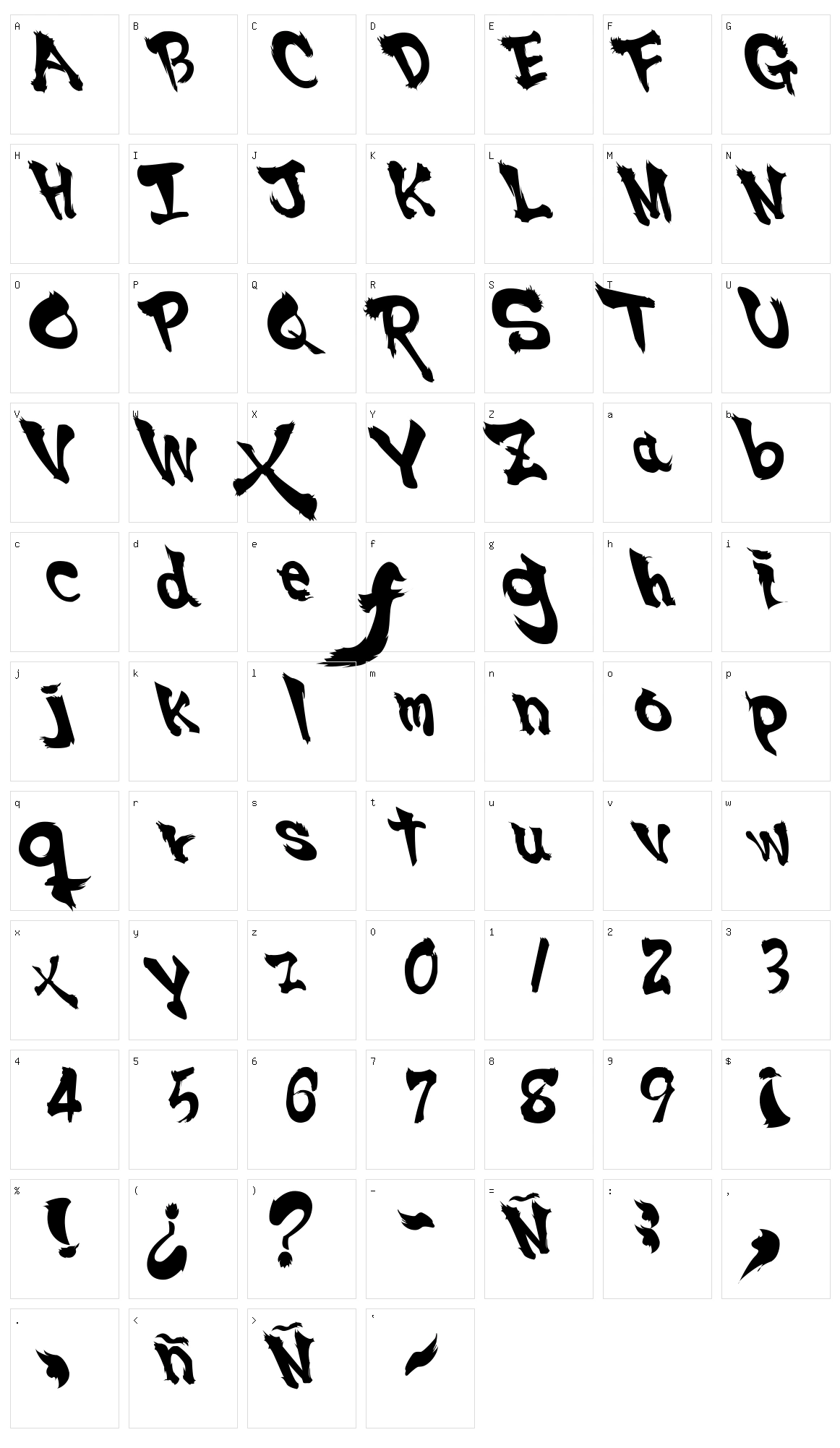
Esta font es una copia d ela dle juego Street Fighter 4
DiseƱada puesto que en ningun lugar de internet hay esta font
y aparte q capcom no suelta su fuente
algunos caracteres fueron creados x mi....